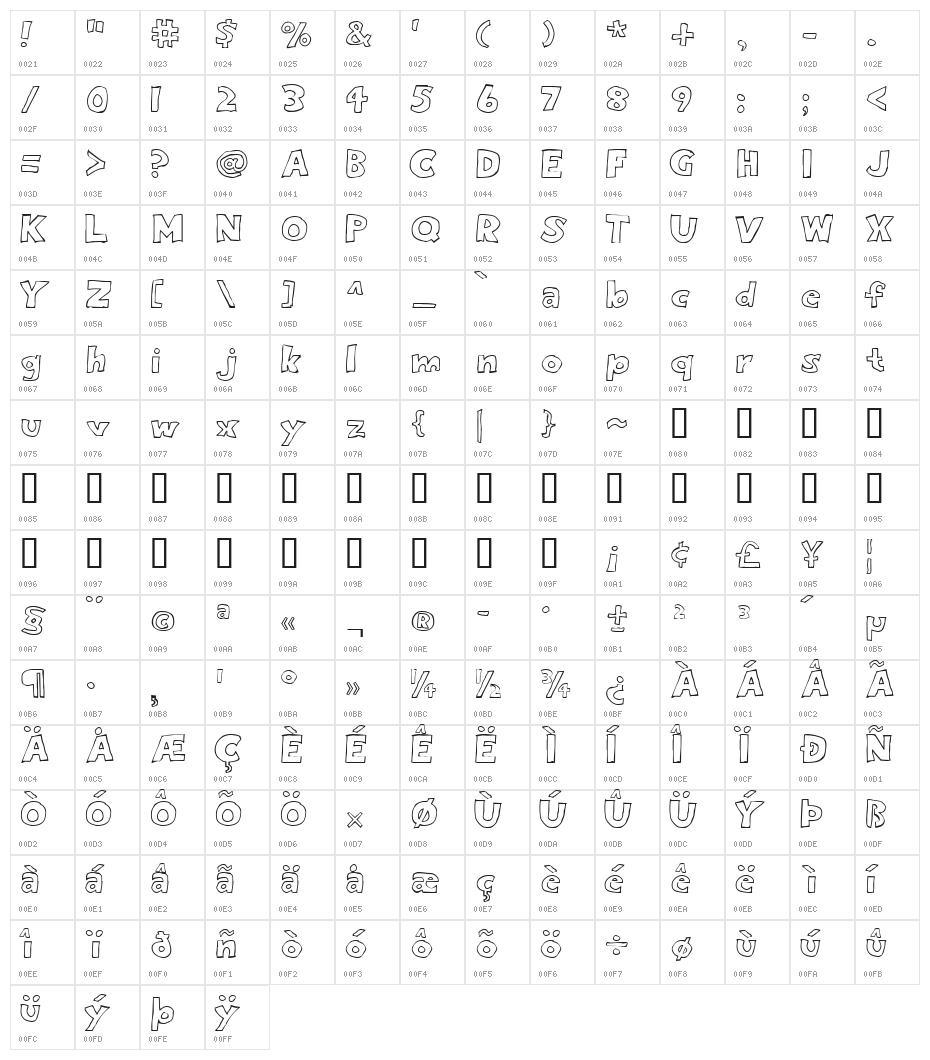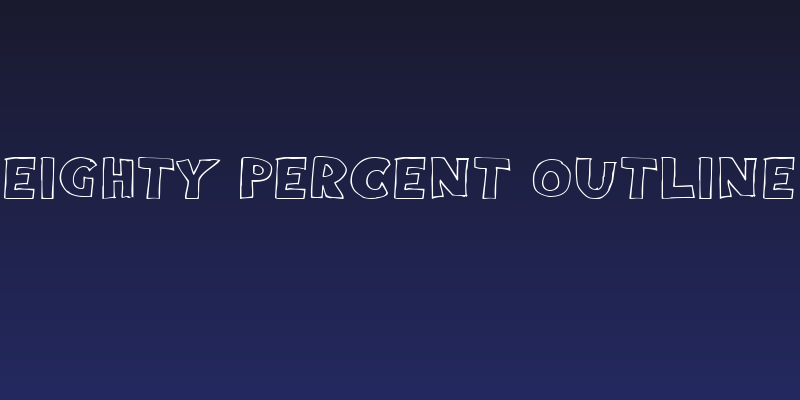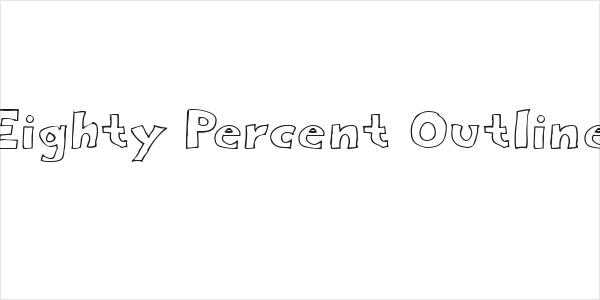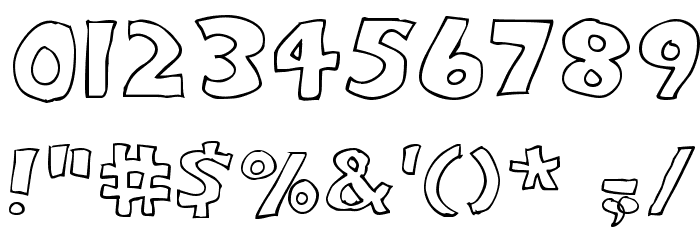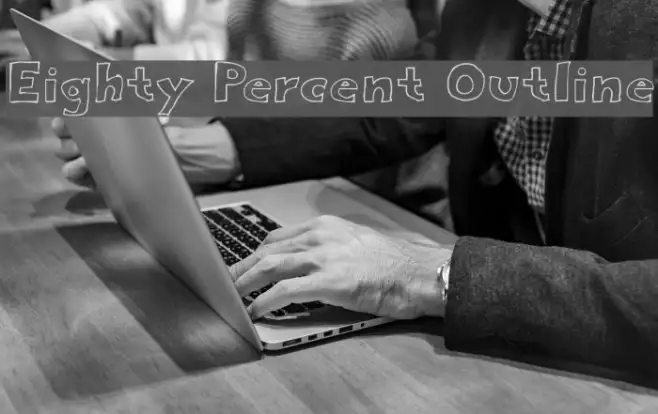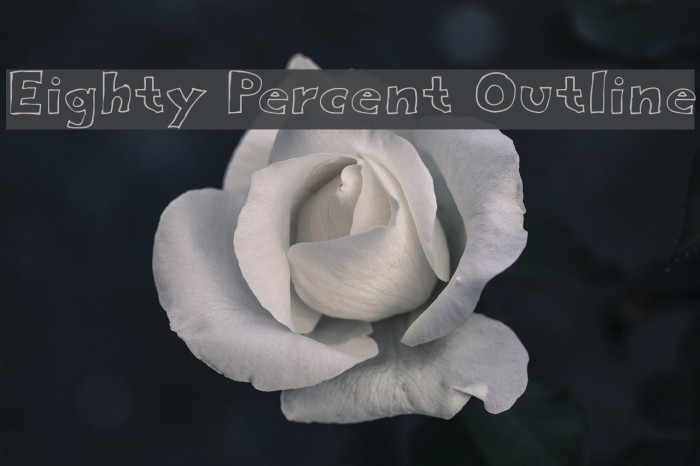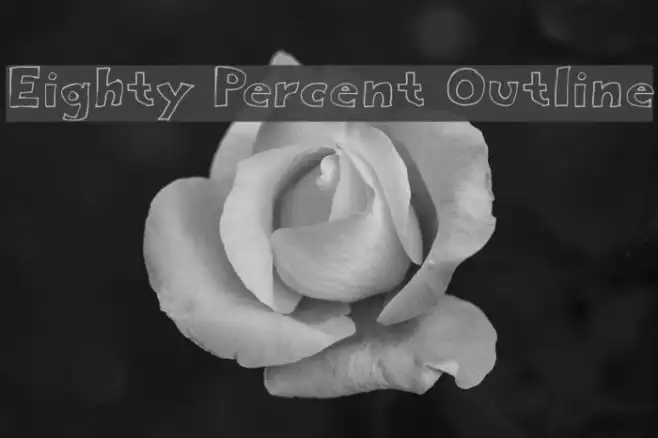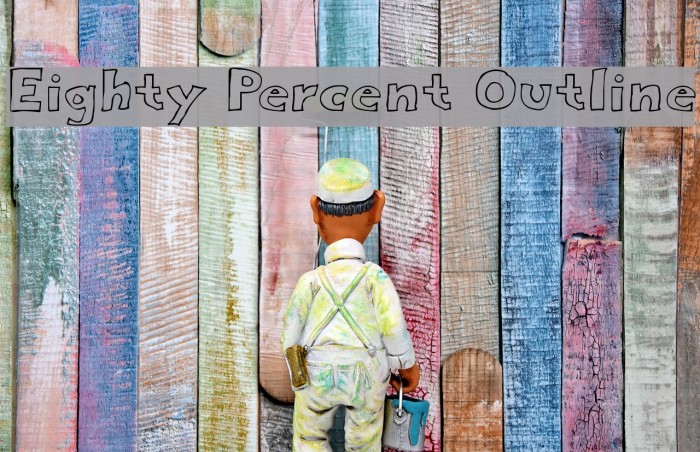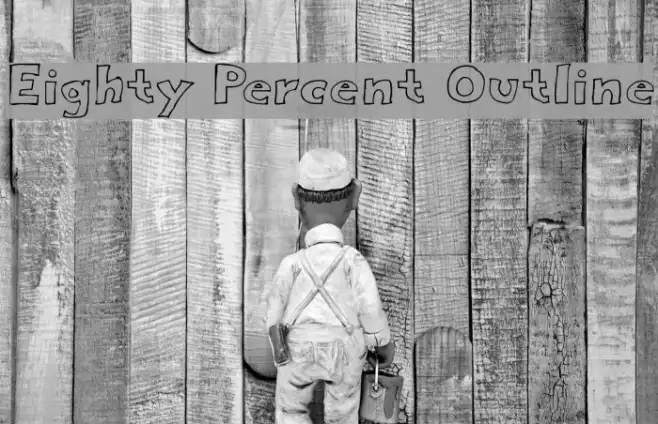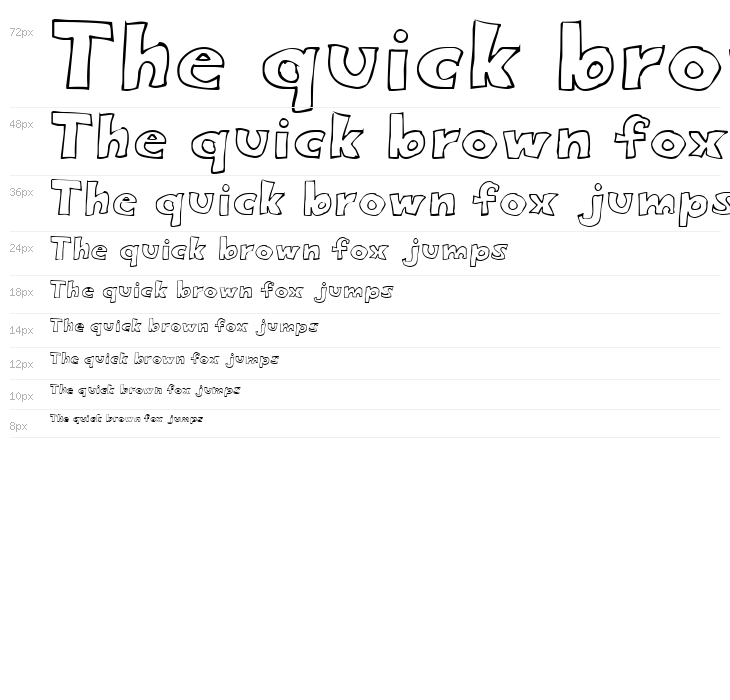
Eighty Percent Outline Font
✎ Outline
| Catégories | Outline |
| Style général | Playful, Whimsical |
| Cas d'utilisation | Headlines, Posters, Branding |
| Projets proposés | Ideal for children's books, comic strips, playful branding, and creative posters. |